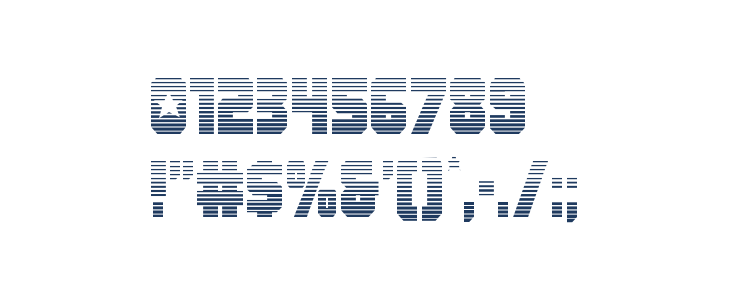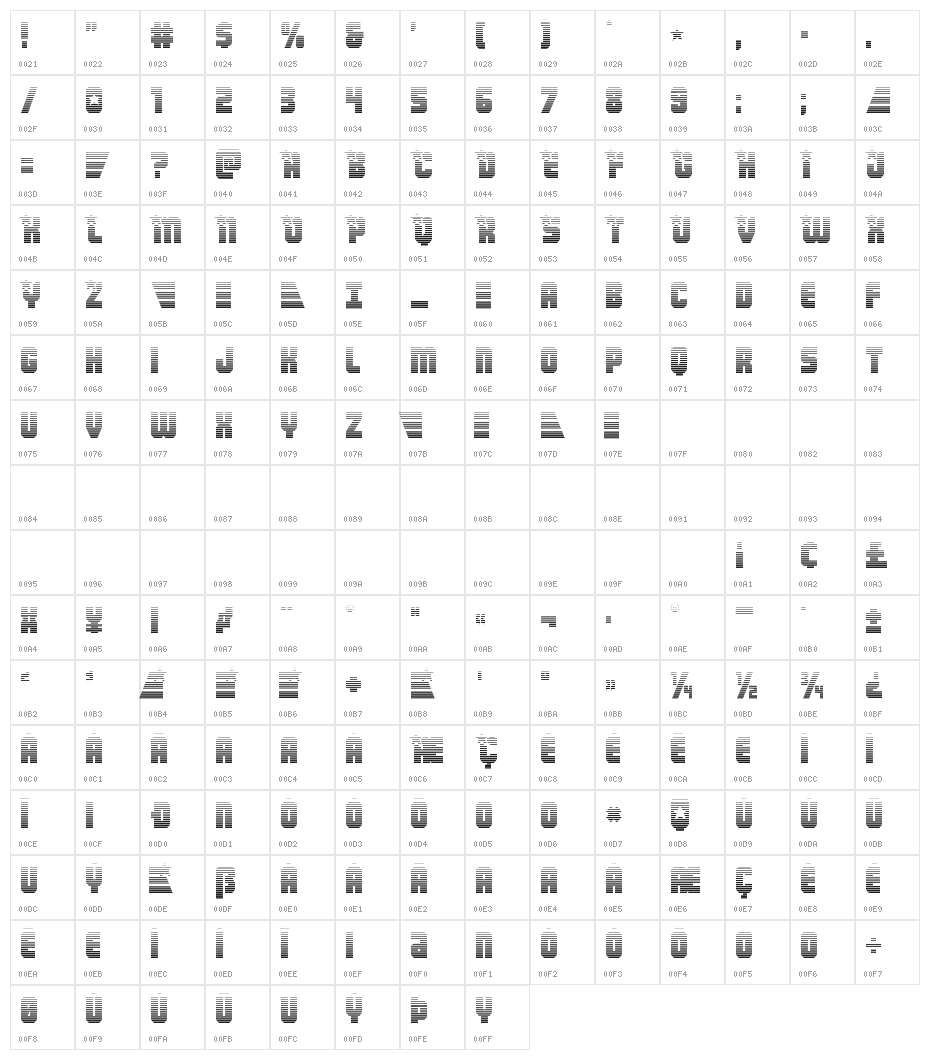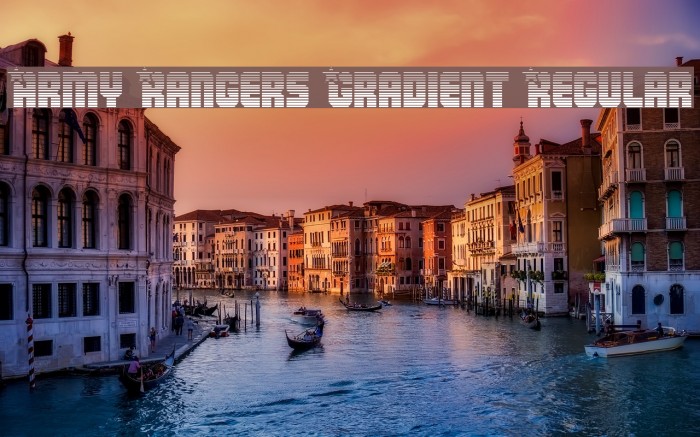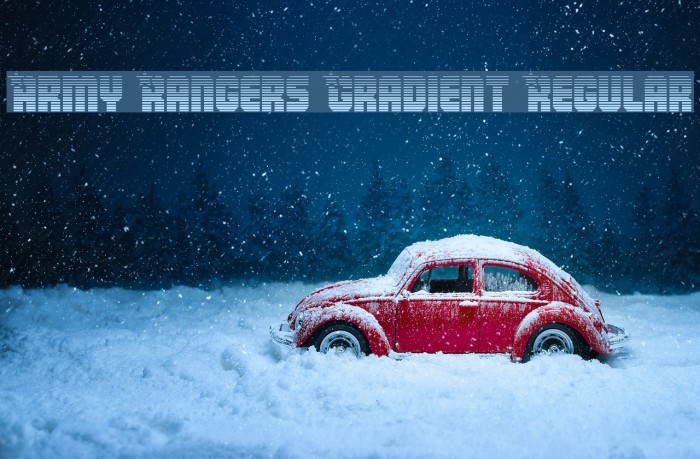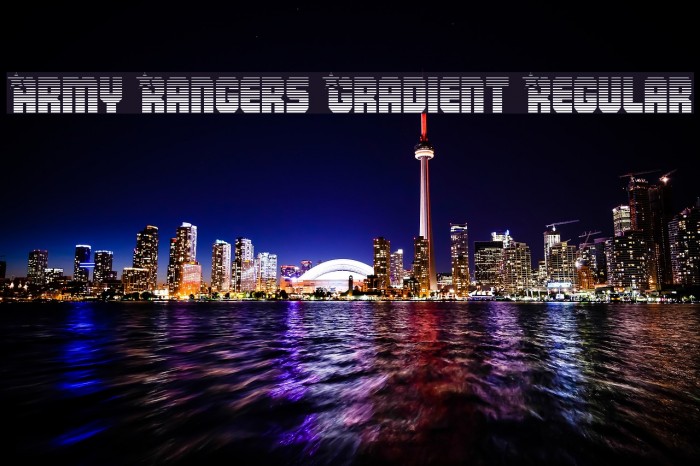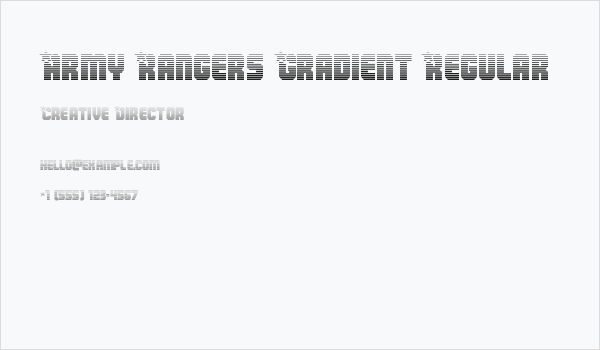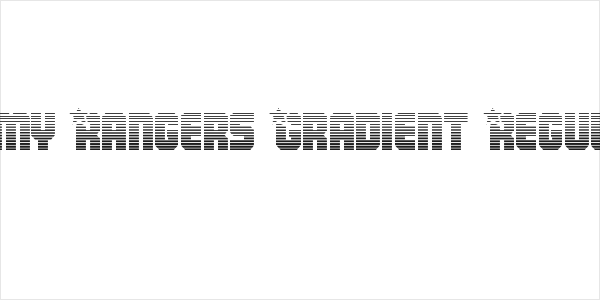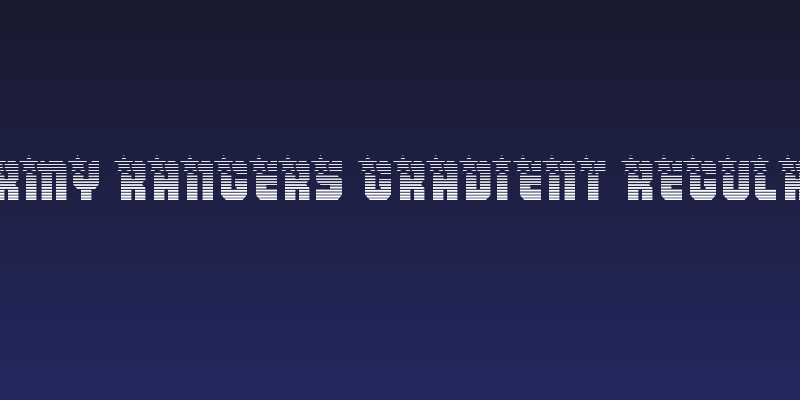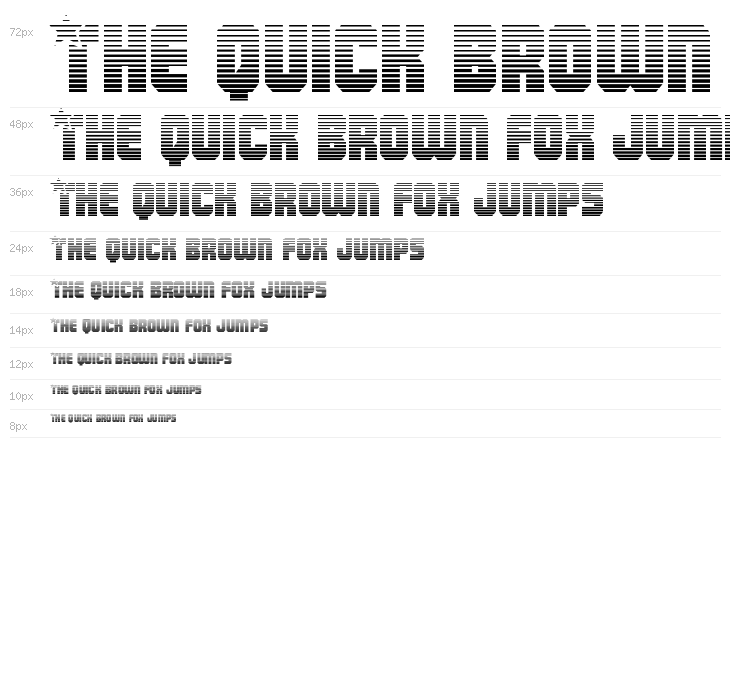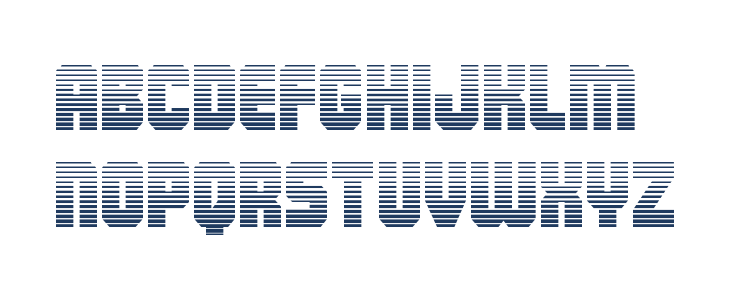
Army Rangers Gradient Regular Font
| Projets proposés | Suitable for military-themed posters, industrial design projects, branding for sports teams, or any project needing a bold, authoritative look. |